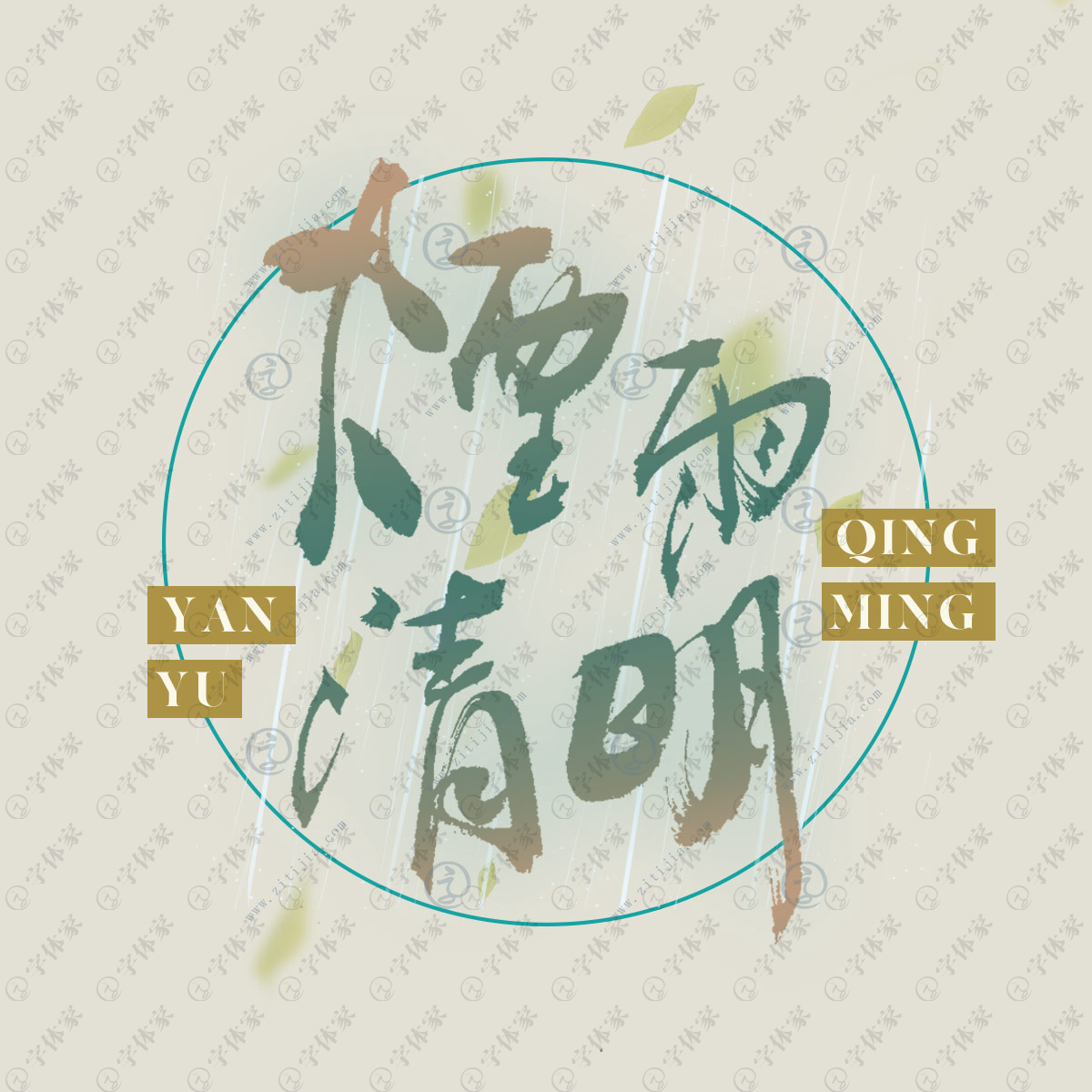
清明,二十四节气之一,春季的第五个节气。太阳到达黄经15°,便为清明。清明时,气清景明,万物皆显,因此得名。清明,既是节气,又是节日。节气的清明,是春耕春种的大好时机;节日的清明,是民间寄放情感和慰劳自己的传统日子。清明节气在时间和天气物候特点上为清明节俗的形成提供了重要条件。
时至清明,中国大部分地区的天气就不冷了,进入到春季。此间的天气,南方与北方好似两重天,北方干燥少雨,南方湿润多雨。 清明最开始是一个很重要的节气,清明一到,气温升高,正是春耕春种的大好时节,故有“清明前后,种瓜种豆”。“植树造林,莫过清明”的农谚。